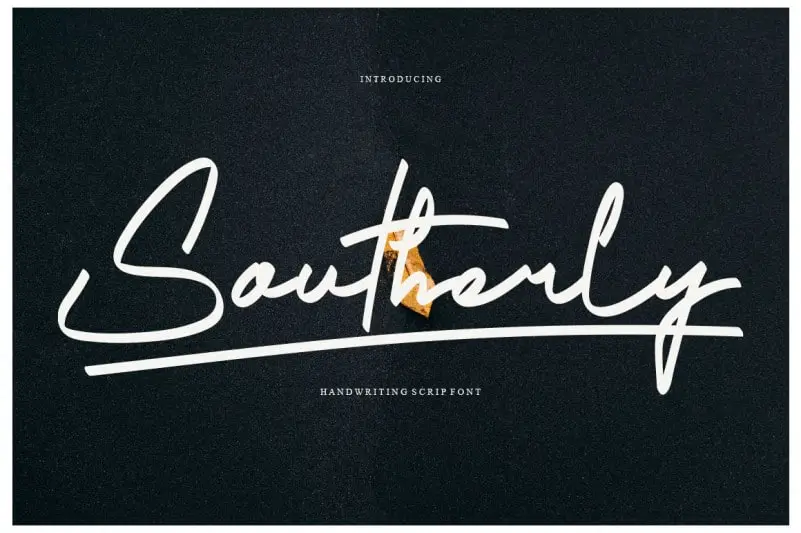
Southerly Script Font – Download Grátis
A Southerly Script Font é uma fonte escrita a mão delicada e fina, com características círculo-pontudas típicas do gosto antigo. Este ligeiro estilo de fonte se destaca por ser ideal para trabalhos que buscam um toque suave, alegre e romântico sem esforço. Perfeito para criações onde uma pequena dose de elegância não causa exagero, esta fonte dá ao design um ar mais amigável e moderno. Combinada com as muitas ideias de design criativas, ela enriquece qualquer projeto, tornando-o único e singular. Seja para cartazes, editoriais, ou mesmo em simples mensagens pessoais, a Southerly Script traz uma vibe descontraída e delicada que certamente conquistará seu público. É perfeitamente ajustada para designers apaixonados por uma estética que remete ao passado, sem perder o toque moderno e único necessário para se destacar.